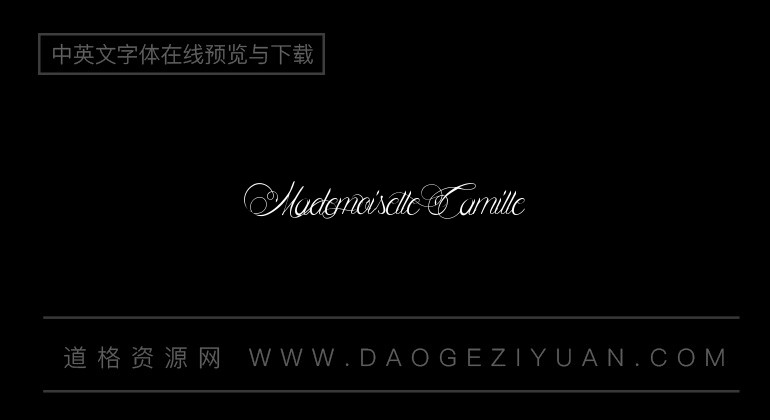
Mademoiselle Camille
Mademoiselle Camille 是一款优雅、精致的手写风格字体,由 Béla Frank 设计。它的流畅曲线和细腻的笔画使得它成为文本、标题或标志等设计项目的理想选择。 Mademoiselle Camille 字母的结构优美,形态自然,像是由一支细长的笔画而成,整体风格略带复古和女性化的气息。这款字体支持多种语言和字母表,包括西欧语言、中欧语言和斯堪的纳维亚语言等。 总的来说,Mademoiselle Camille 字体适合用于女性、时尚、美容、艺术、文化等相关领域的设计项目中,它能够为设计师带来一种独特的视觉风格和品牌形象。
Mademoiselle Camille是一款非常不错的手写艺术字体,具有很好的视觉感,适合于文化类的宣传设计、商业类品牌的广告和产品包装设计以及个性化文字排版等较多场景。